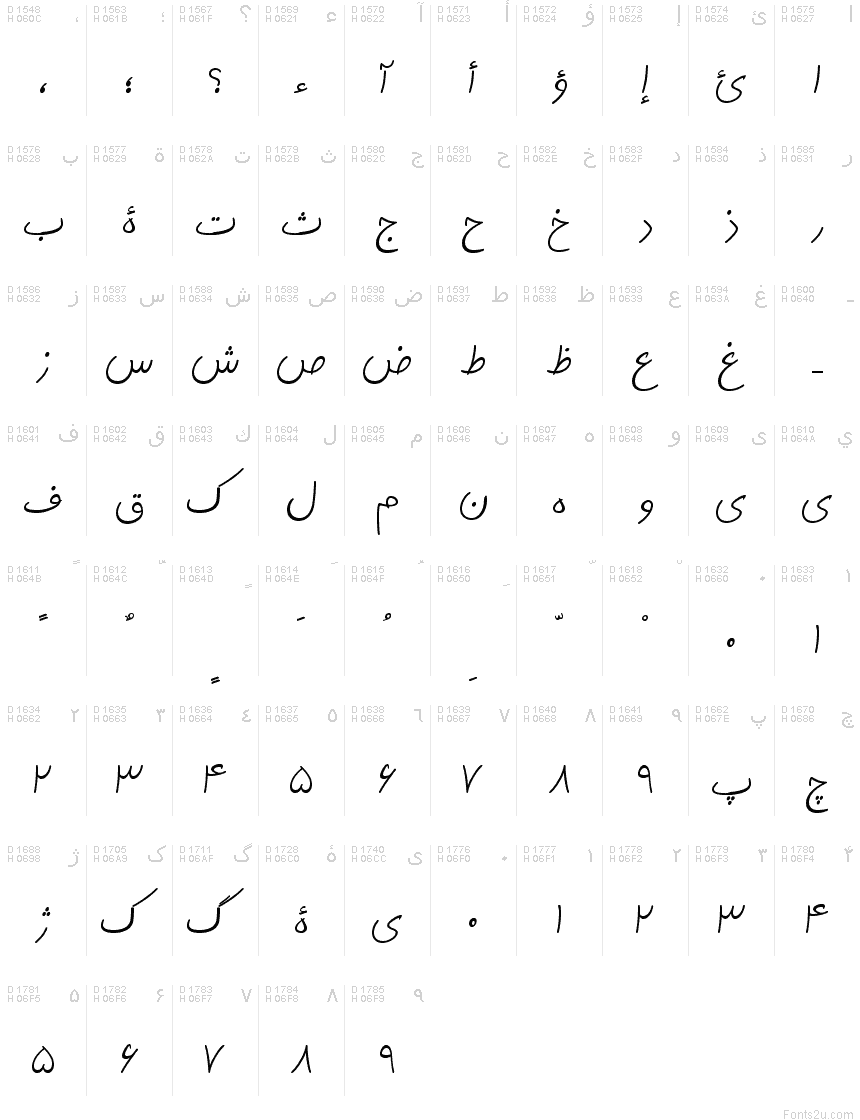
B Kamran von Borna Rayaneh ist eine kostenlose arabische Display-Schrift mit einem kompakten, kalligrafischen Rhythmus. Die Buchstaben wirken kräftig und handschriftlich statt formell, mit abgerundeten Verbindungen, schwungvollen Kurven und einer dichten, zusammenhängenden Textur, die kurzen Wörtern eine präsente und selbstbewusste Ausstrahlung verleiht.
Dieser Charakter macht die Schrift ideal für Kulturplakate, Buchcover, Musikverpackungen, Titelkarten und markante Überschriften, bei denen das Schriftbild selbst für die Stimmung sorgt. Als kostenloser Font eignet sie sich am besten für kurze Display-Anwendungen, redaktionelle Highlights und Logo-Schriftzüge – besonders dann, wenn Sie arabische Schriftzeichen suchen, die warm, traditionell und direkt wirken.